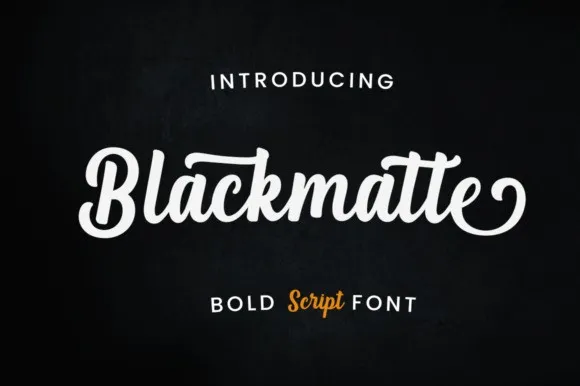
A Blackmatte é uma nova adição para colecionadores de fontes script modernas que buscam uma mistura única entre robustez e nostalgia. Desenvolvida pelo designer 99designs, esta font tem um estilo bold que se destaca, oferecendo um toque nostálgico que faz lembrar os anos 80 ou 90, quando as fãs de gráfica ainda eram muito mais ativas. Com uma densidade perfeita entre fina e grossa, esta font é equilibrada e variada, projetada para destacar o seu próximo projeto visual. O facto da Blackmatte ser PUA (Portable User Access) permite que você facilmente acesse todos os caracteres e “swashes” de maneira conveniente e intuitiva. Sem dúvida um recurso gráfico inovador que enriquece qualquer projeto, seja ele um logo, uma identidade visual ou até mesmo um site web personalizado.